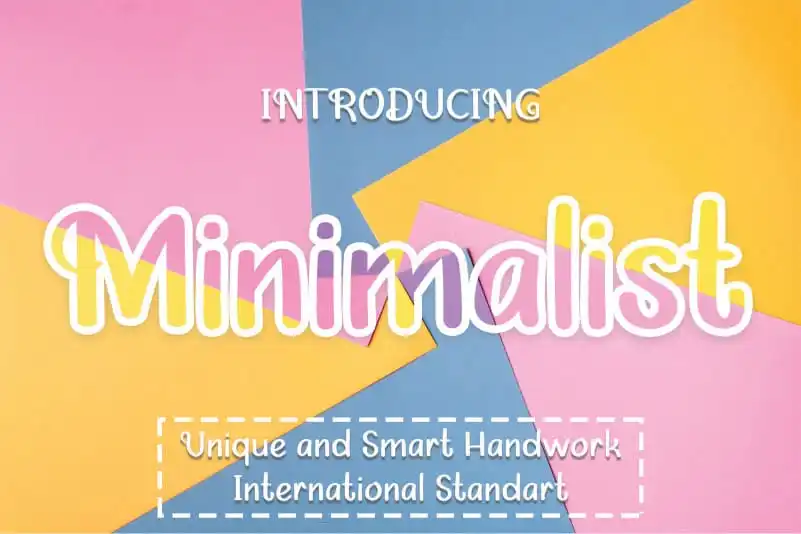
Esta é uma linda fonte à mão livre, elegante e equilibrada, perfeita para incorporar em seus projetos. Com qualquer assunto ou tema, essa fonte se destaca por seu potencial para revestir com beleza até as mais simples criações. Seja um logotipo, uma etiqueta de embalagem ou um texto no site da sua empresa, a Minimalist Font torna o design do produto único e destacado. Ela é perfeita para quem busca uma fonte que seja tanto discreta quanto poderosa, proporcionando um toque refinado sem comprometer a legibilidade. Essa elegância natural faz desta fonte uma escolha ótima para aqueles que valorizam minimalismo em seu design visual, combinando o essencial com o belo. Com ela na sua coleção de fontes, você pode agregar sofisticação e elegância a qualquer projeto, seja ele digital ou impresso.